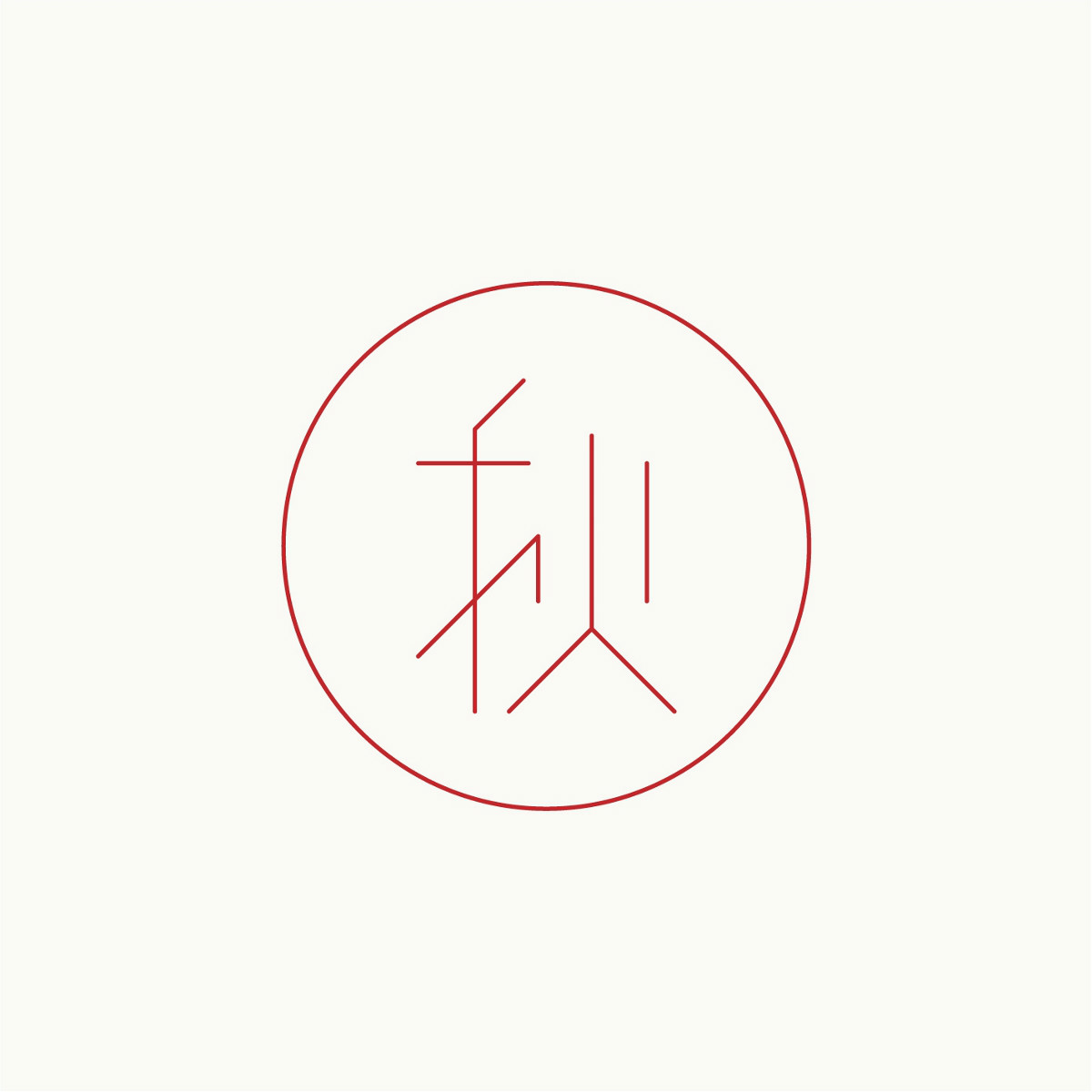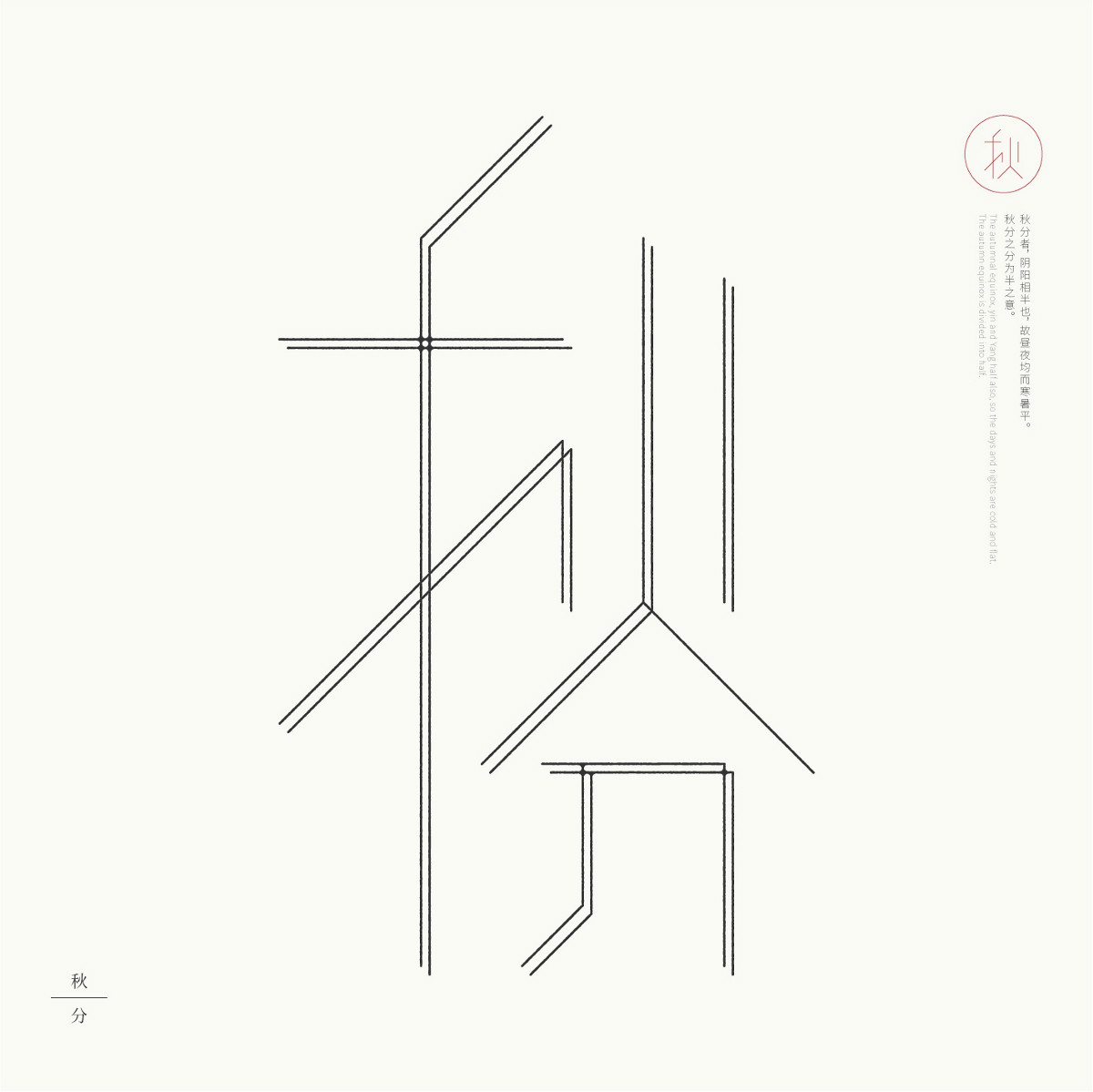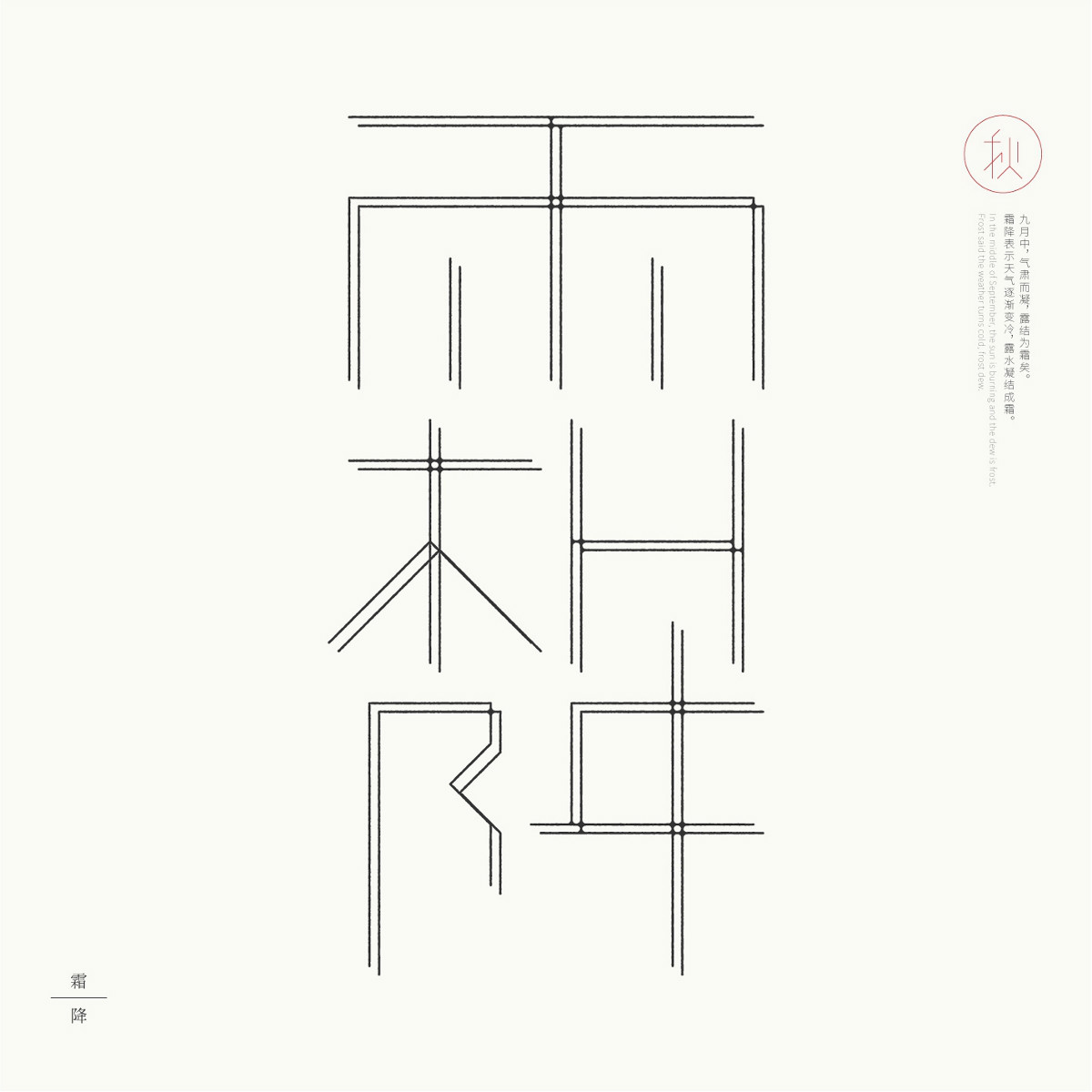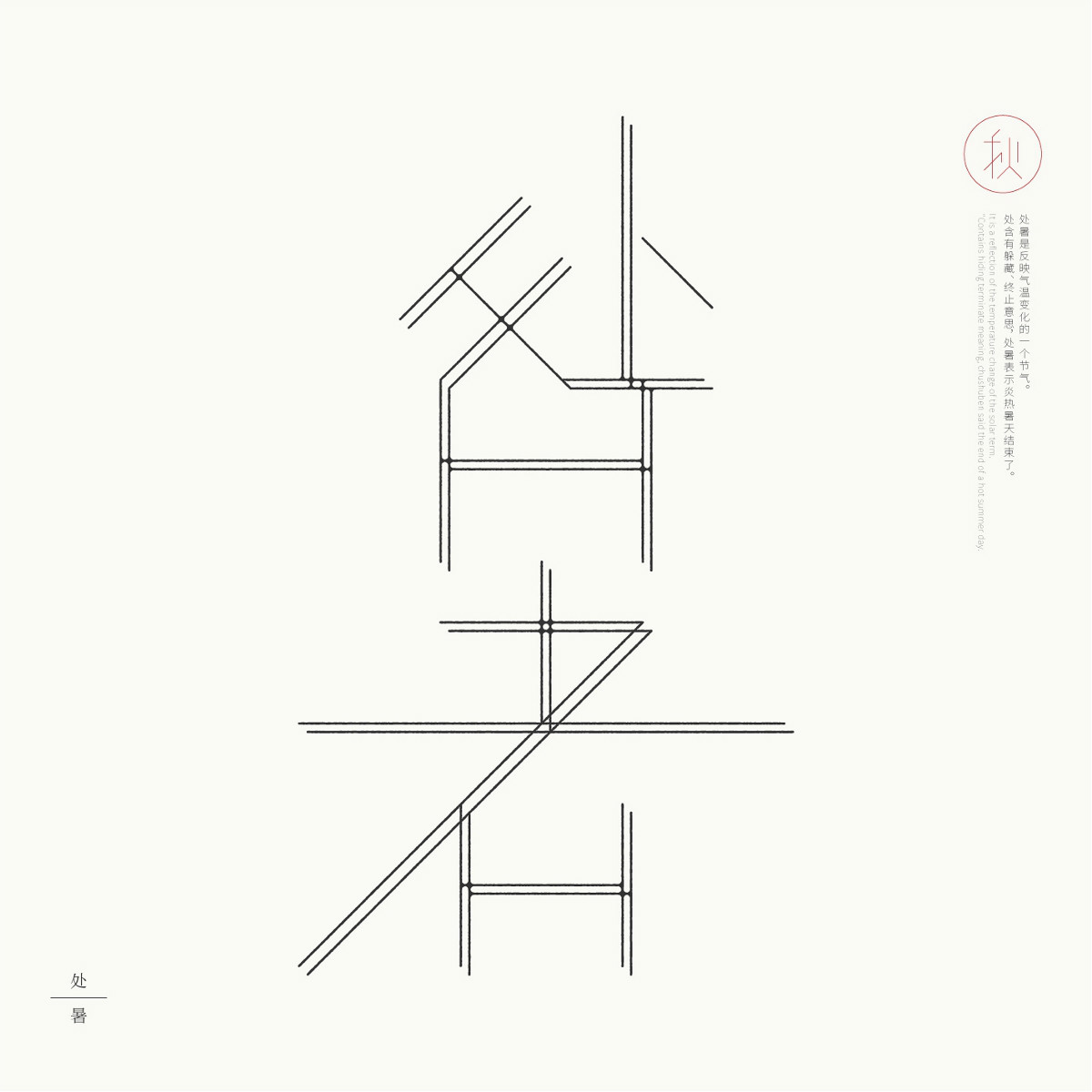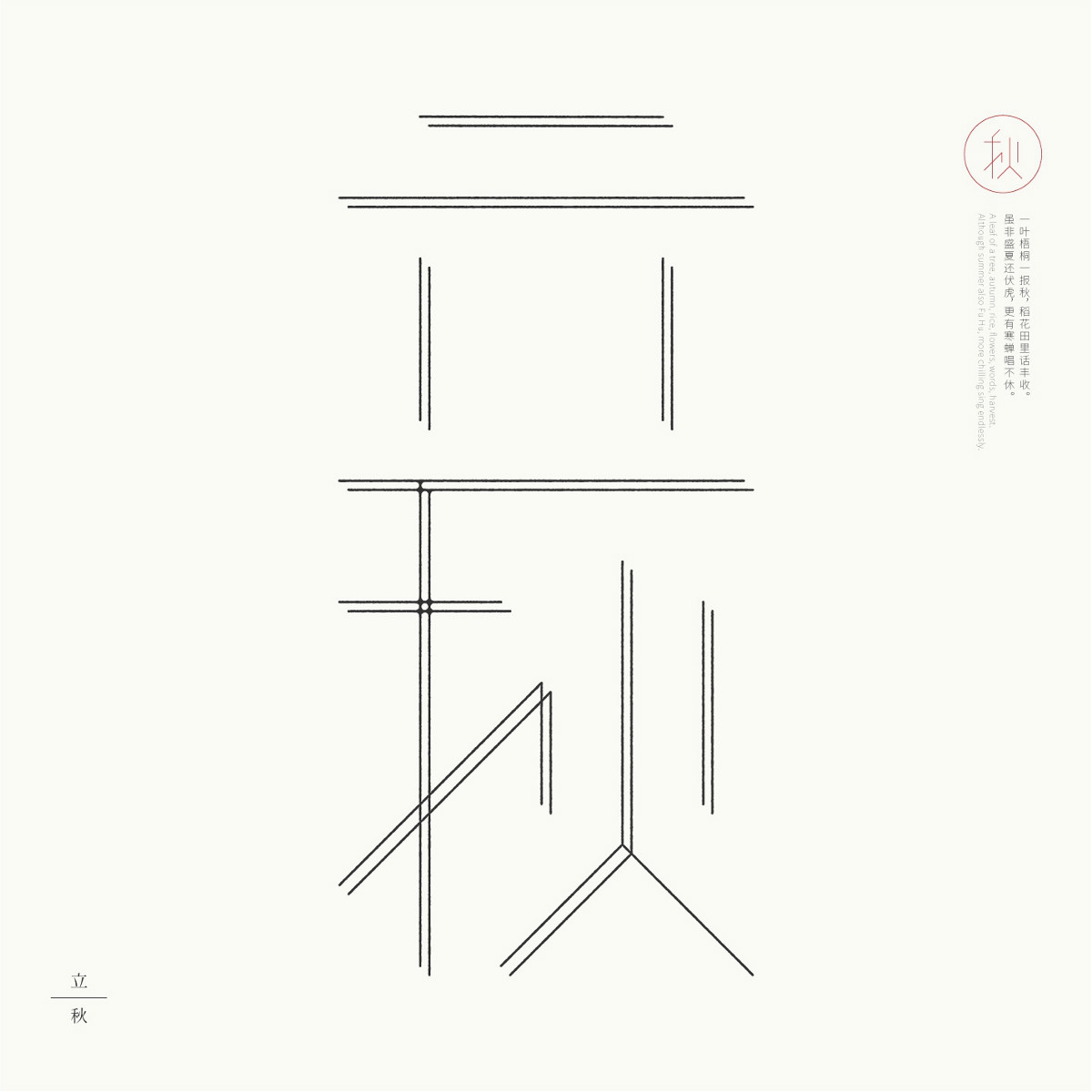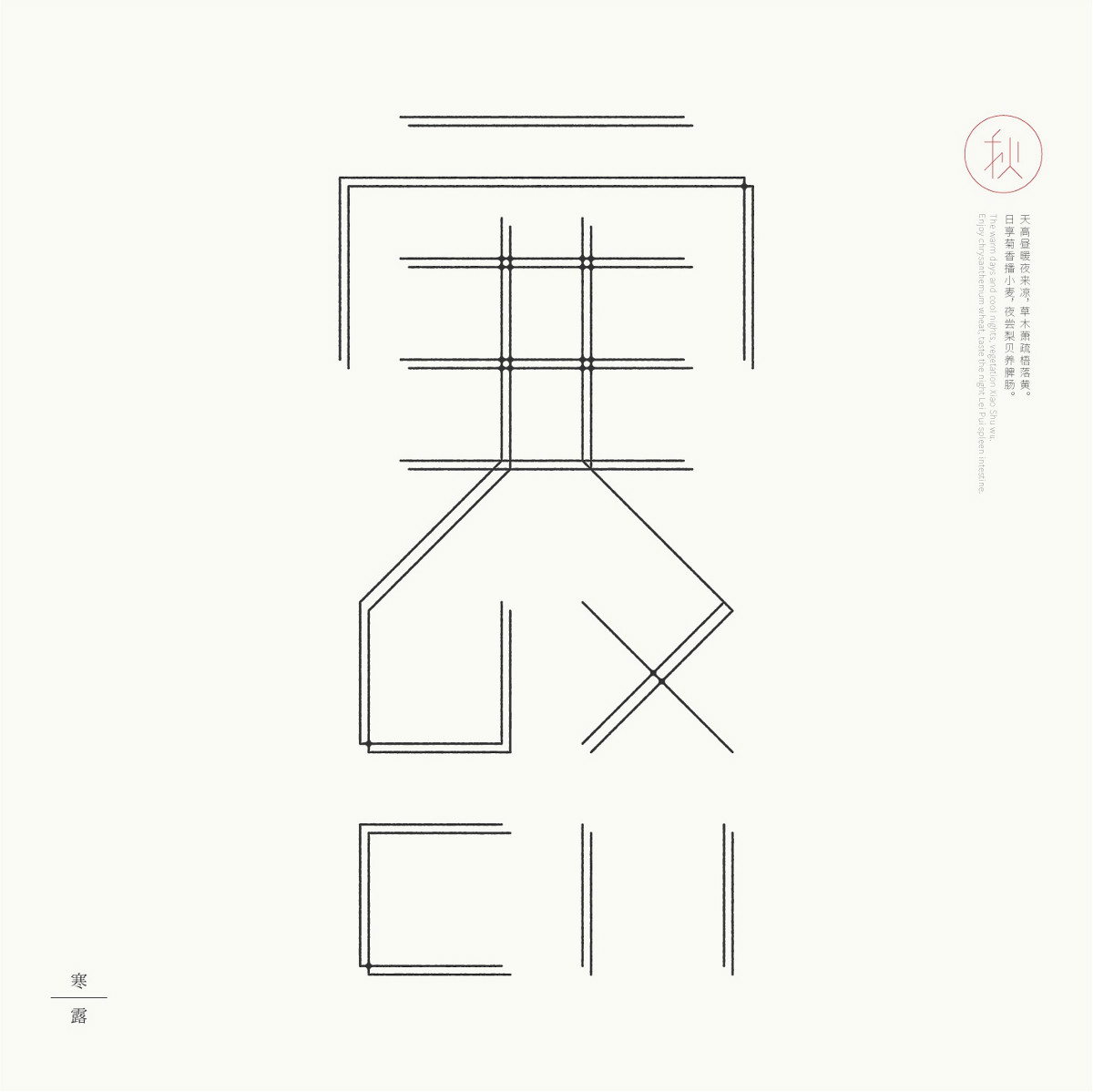
24節(jié)氣字體設(shè)計(jì),簡約黑白藝術(shù)字體設(shè)計(jì)
24節(jié)氣字體設(shè)計(jì),簡約黑白藝術(shù)字體設(shè)計(jì)24節(jié)氣字體設(shè)計(jì),簡約黑白藝術(shù)字體設(shè)計(jì)
24節(jié)氣字體設(shè)計(jì),簡約黑白藝術(shù)字體設(shè)計(jì)